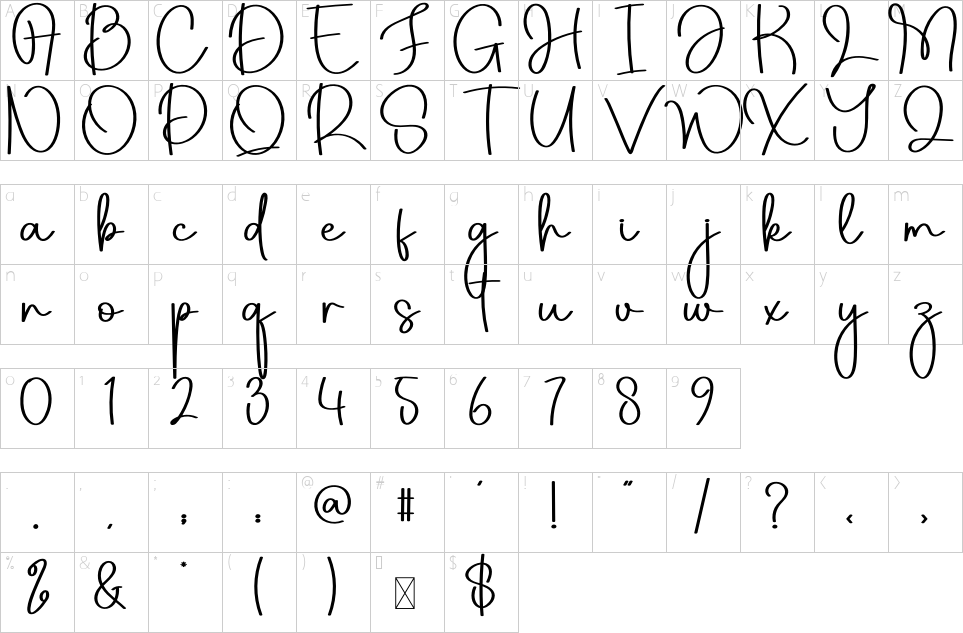
A fonte Delightful é uma descoberta para fãs do bom gosto e designers versáteis. Desenhada por scratchones, essa elegante e minimalista fonte foi criada para agregar um toque especial às suas criações digitais. Com seu design arredondado e delicado, Delightful adiciona um charme natural que se encaixa perfeitamente em variados projetos de layout digital. Não é uma fonte complexa demais, mas também não é básica o suficiente para desqualificar a beleza de Delightful. Em menos de cinco cliques, você pode começar a usar essa fonte livremente no Windows e Mac, criando designs únicos e pessoais que expressam sua personalidade. Com apenas 469 downloads desde seu lançamento, esta fonte é uma jóia rara para qualquer coleção de recursos gráficos disponíveis. Delightful não só oferece beleza, mas também um toque único e sofisticado a seus trabalhos.